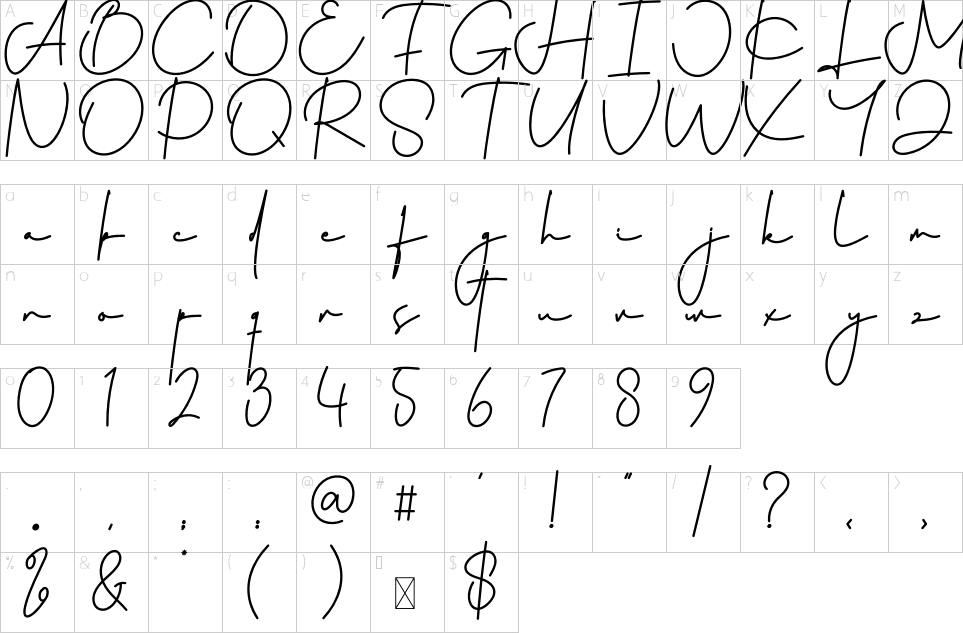
A Santa Signature é uma elegante fonte de签字风格,专为需要一种温馨和优雅的字体而设计。这种字体非常适合用于商业标识、社交媒体帖子或任何需要一种节日氛围的项目。特别适合装饰与圣诞主题相关的设计,如圣诞卡片、贺卡或节日装饰。设计师scratchones凭借其细腻的手工技艺,为Santa Signature添加了独特的笔触和细节,使它成为一种独特的选择。自2018年发布以来,Santa Signature已被下载超过350次,表明它受到设计爱好者的广泛欢迎。不论是节日装饰还是日常文案,Santa Signature都能为你的项目增添一抹温馨的气息。现在,就来下载这个免费的、引人注目的字体,让它为你的创作增添一份特别的温暖。